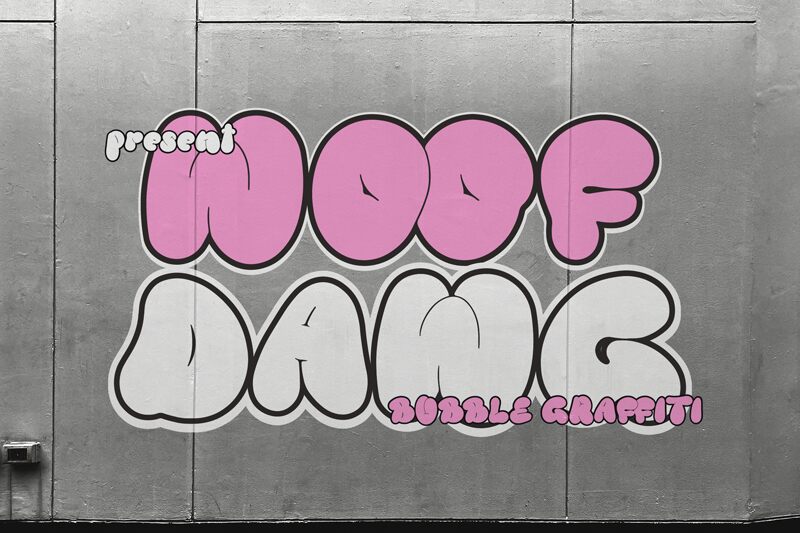
Woof Dawg da Denustudios é uma fonte gratuita de bubble graffiti construída a partir de formas exageradas de bordas suaves, com uma silhueta desenhada à mão intencionalmente irregular e proporções soltas de letra para letra. Recortes internos estreitos dão nitidez às letras que, de outro forma, seriam cheias.
Seu ambiente mais forte é a criação de marcas de streetwear, onde as formas densas podem transformar um nome em uma marca compacta semelhante a uma tag. O mesmo volume lúdico também se adequa a produtos de skate, pôsteres de música e gráficos de eventos voltados para o público jovem, especialmente quando as letras passam a fazer parte de uma cena ilustrada. Em todos esses usos, o fio condutor é uma atitude urbana caricata que parece mais um emblema desenhado do que um tipo de exibição convencional.